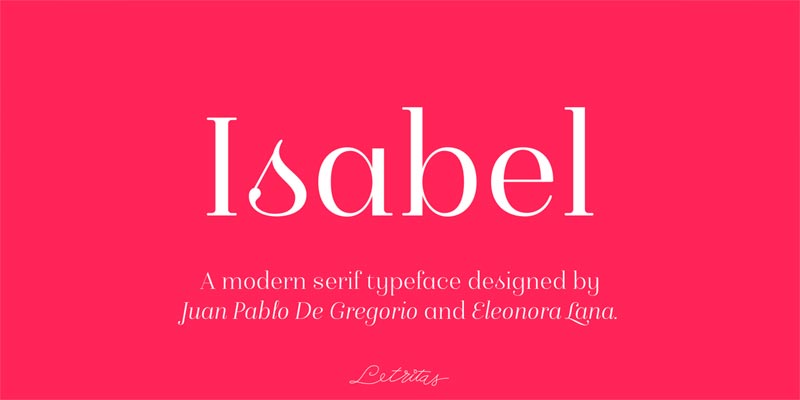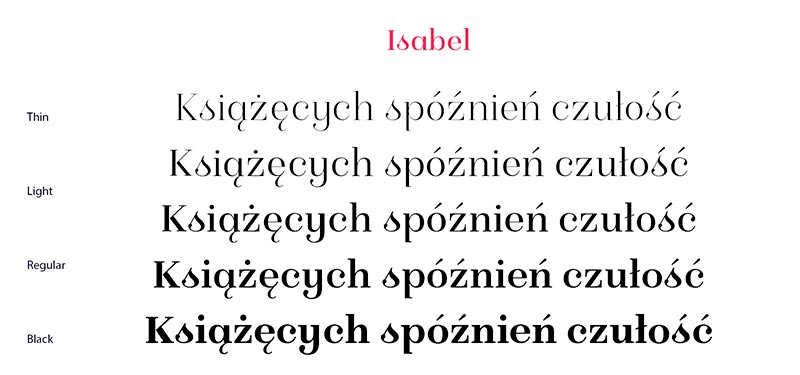
Font Isabel
Zakupiliśmy rodzinę fontów szeryfowych Isabel. Font charakteryzuje się wysoką czytelnością i wesołym charakterem, dzięki czemu nadaje się idealnie do składu materiałów przeznaczonych dla dzieci. Zestaw posiada polskie znaki diakrytyczne.